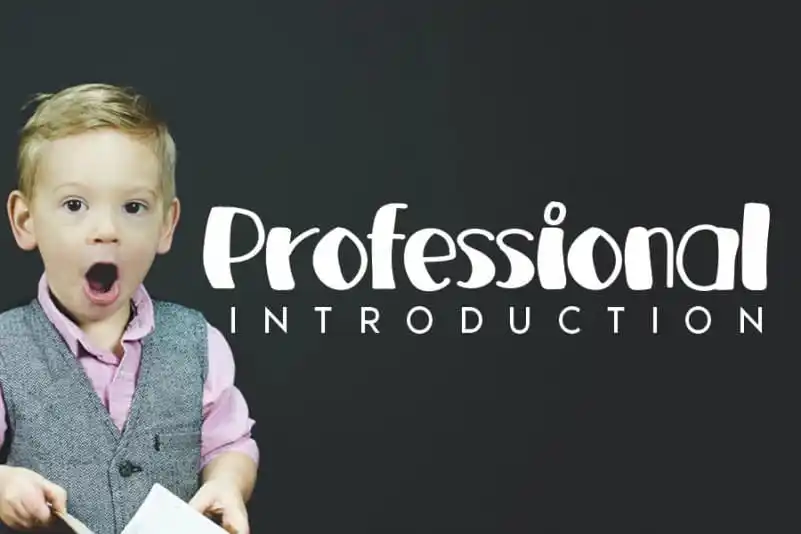
Professional Handwritten Font – Fonte Grátis
Professional Handwritten Font
Esta Professional Handwritten Font foi criada para quem busca uma mistura única de elegância e autenticidade. Embora seja uma tipografia escrita a mão profissional, sua expressividade permite um toque divertido e inovador que tornam qualquer conceito criativo destoante. Seja para uso em títulos de apresentação, rótulos de produtos ou até mesmo em design gráfico pessoal, esta fonte transmite seu sabor autêntico e original. Ela combina perfeitamente tanto com projetos formais quanto com criações mais criativas, tornando-a uma opção ideal para aqueles que valorizam a personalidade única de suas obras. Específicamente, o Designer andikastudio trouxe à vida esta fonte através de sua habilidade de capturar as nuances e expressividades humanas na escrita. O resultado é uma ferramenta de design versátil e encantadora para quem busca um toque pessoal em seu trabalho.